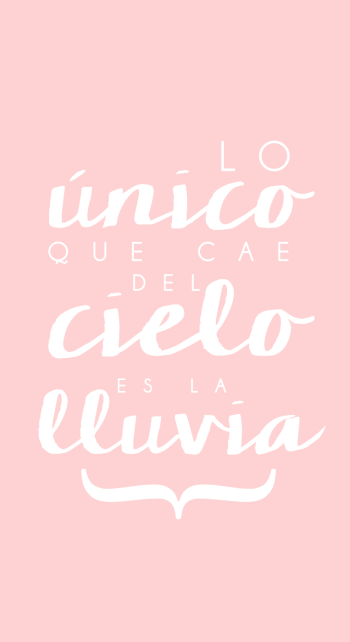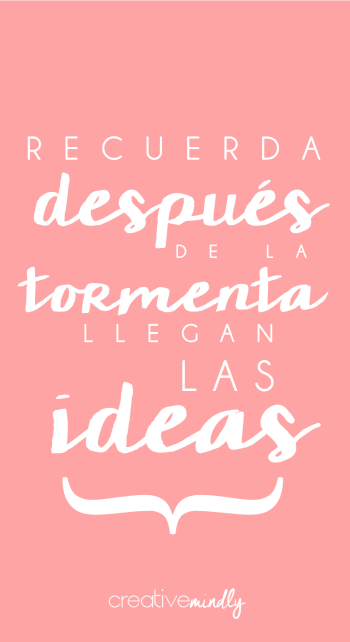
Quiero ofreceros 5 tipografías, yo creo que las más codiciadas. Esas por las que recibo mil emails preguntándome cuáles son y de dónde las he sacado. Se tratan de cinco tipografías hechas a mano, que son lo más de lo más ahora mismo. A mi me gustan muchísimo y espero que a vosotros también. Así que os dejo la imagen y justo debajo los enlaces para que podáis descargarlas. Pero no robéis y os marchéis, más abajo os cuento más cosas que seguro que os van a venir estupendamente.